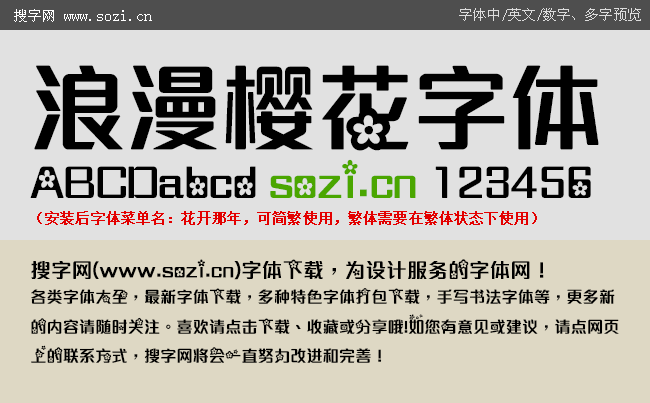
浪漫櫻花字體
搜字網(wǎng)給大家提供一款很可愛(ài)的手機(jī)中文字體下載。字體名叫浪漫櫻花字體,這款手機(jī)字體是以藝術(shù)變形后的黑體字體為原形,筆畫(huà)間插入了卡通櫻花圖案?ㄍㄎ短貏e濃,是一款非?蓯(ài)的卡通字體,特別適合喜歡手機(jī)字體個(gè)性一些的朋友在手機(jī)上安裝使用。